20 多種最佳免費大寫字母字體
已發表: 2019-11-06排版是設計的關鍵元素,影響美學和可訪問性。 在設計廣告、標題或標牌時,您需要一種引人注目的字體,並且可以立即創建層次結構。 塊字體適合複製必須突出的關鍵圖形區域。 但是,它們不應該用於大量文本。 讀者發現在如此突出的字體中閱讀太多單詞很費勁。
塊字體屬於廣泛的排版類別,適用於標牌、標題和其他短文案、引人注目的設計領域。 傳統上,塊字體的筆劃將具有相同的粗細,但在其中一些更具藝術感的字體中,較薄與較厚的區域賦予它們個性。 塊字體也有硬角、很多直線並且通常都是大寫的。
這裡有 20 種最好的大寫字母字體,可以免費下載用於個人或商業用途。
1.降臨臨
這種現代的無襯線字體設計纖薄,樣式多樣。 它在單色或單色背景上看起來特別引人注目。
2. 年齡
圓潤和結構化,Age 最酷的特徵是字母的截尾(如小寫的“g”和“y”)。 這種超厚、類似空間的字體最適合非常引人注目的圖形設計,包括徽標。
3. 停電
只有當您想要一個大到幾乎可以聽到它的標題時,才應該使用停電。 這種面對面字體的設計師的靈感來自報紙標題中字母孔的著色。
4.大塊
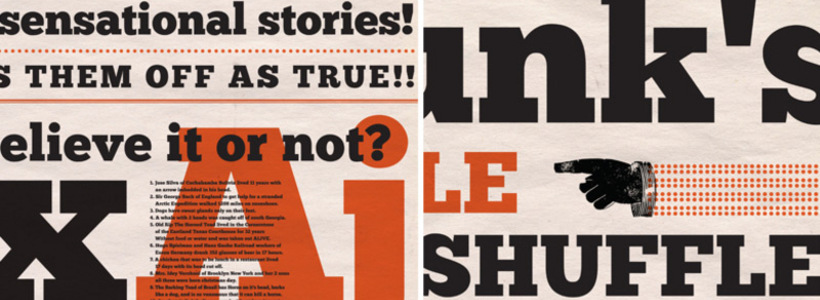
超大膽的 Chunk 引人注目,外觀經典。 被描述為美國西部與報紙標題相遇,最好搭配更纖細的字體。
5. Coolvetica
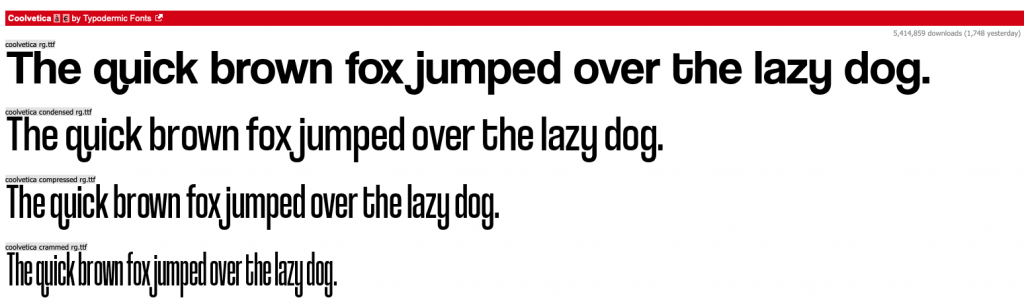
這種對 Helvetica 的俏皮修改具有緊密的間距和時髦的捲發。 該字體是對 1970 年代的致敬,特別是那個時代美國連鎖店的標牌。
6. 新生
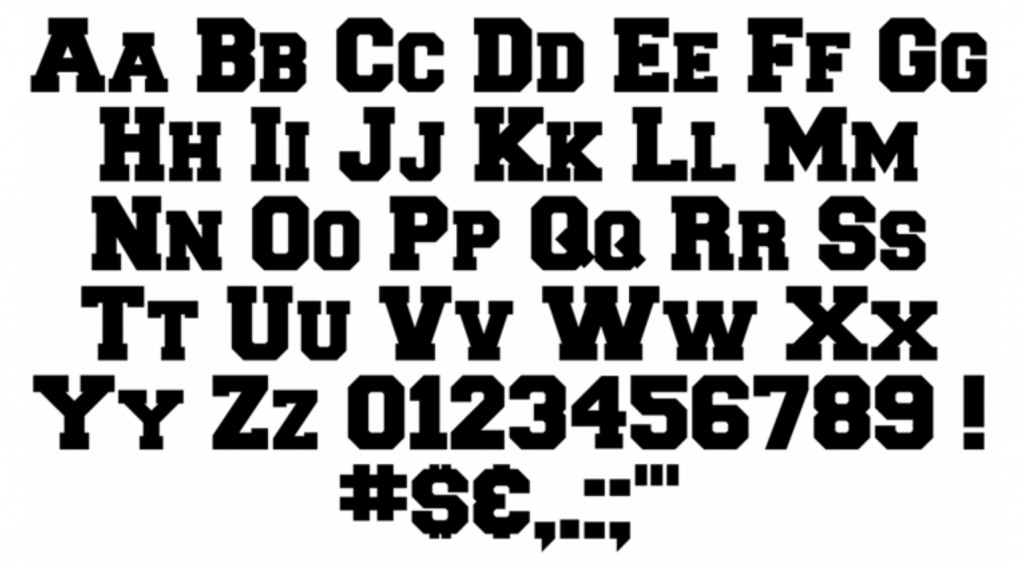
Freshman 是一種簡單的大學風格字體,帶有寬大的粗體字母。 小寫字母在技術上仍然是大寫字母,只是尺寸更小。 如果您想要更苗條的新生版本,請查看美國研究生或高中。
7. 加博
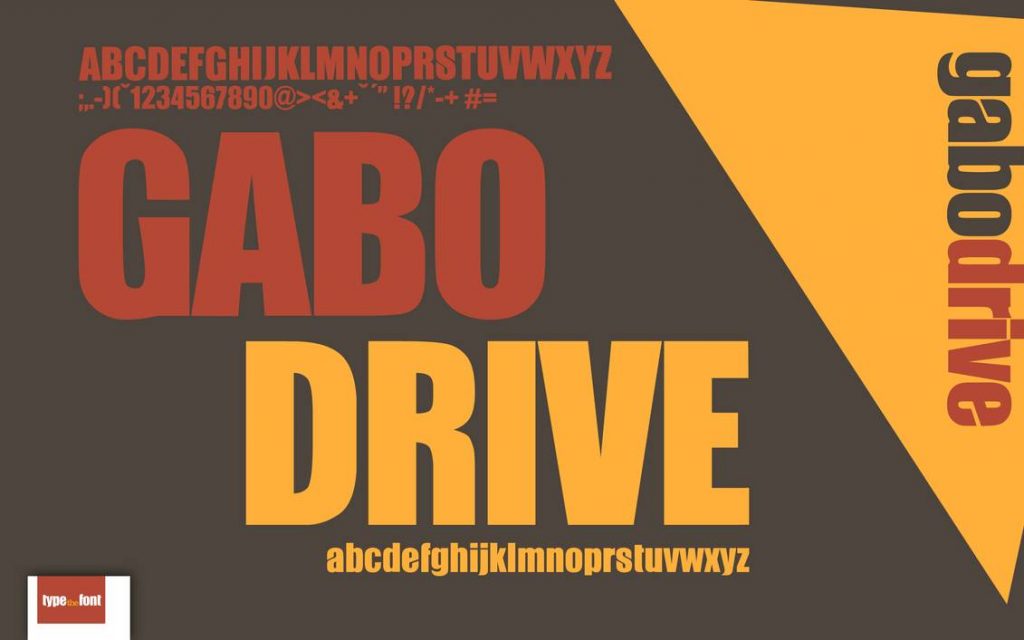
你認為你以前在電影海報上見過加博,也許你見過,但如果你仔細觀察,有些字母會有微妙的傾斜。 在小寫字母中,字母具有平滑的曲線和輕微的裂縫。
8.五大湖
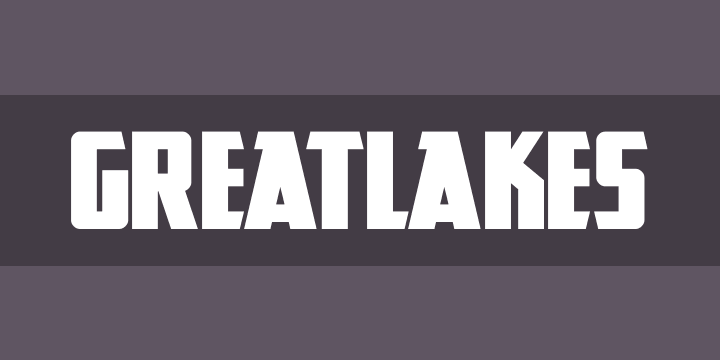
由於某些字母的急劇傾斜和切割,GreatLakes 有棱有角且具有很高的高度和力量,看起來像是在向前走。 它的名字也很完美,你可以在戶外商店的標誌上畫上它。
9. 更高
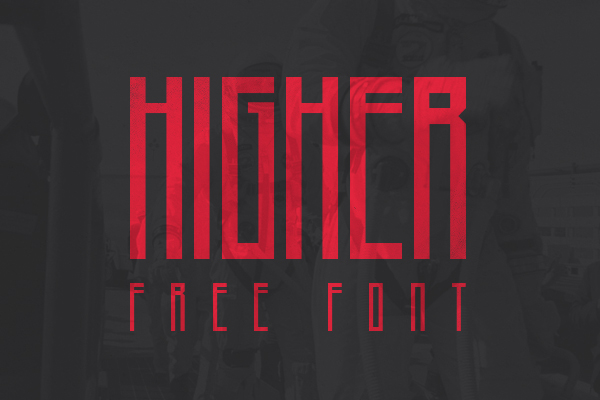
較高是細長和高的,並且字母的識別部分被誇大地高或低。 出於可讀性目的,請確保在確定之前使用此字體測試您的確切副本。
10. 紐波
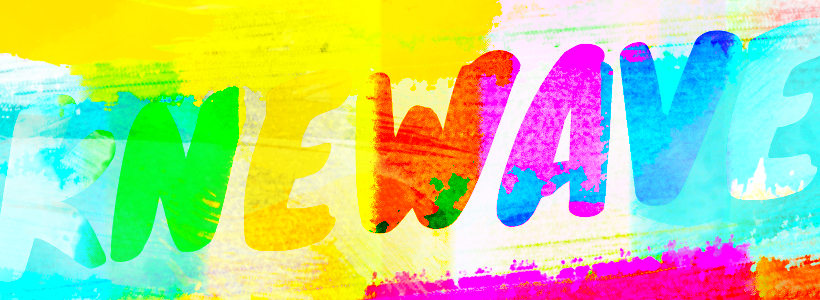
無憂無慮、有趣且大膽,Knewave 是一款適合年輕企業或網站的圓形字體。 這種繪畫字體具有刷狀紋理,沿字母末端最為明顯。
11.小莫田
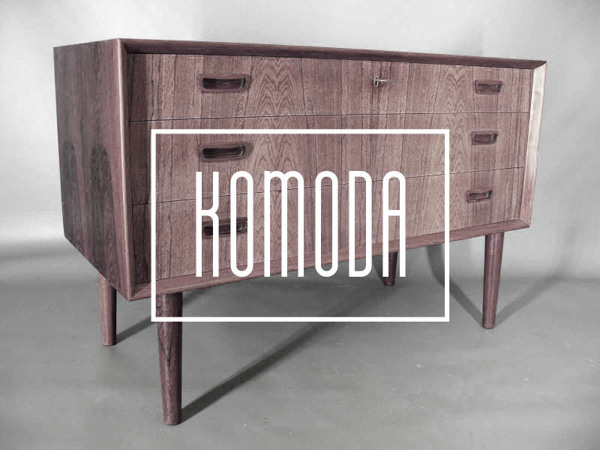
這種窄字體有很多高度,它與短而粗的子標題搭配得很好。 將 Komoda 用於現代或休閒業務,例如極簡主義的家具店或宣傳歡樂時光的酒吧。
12. 馬蒂茲
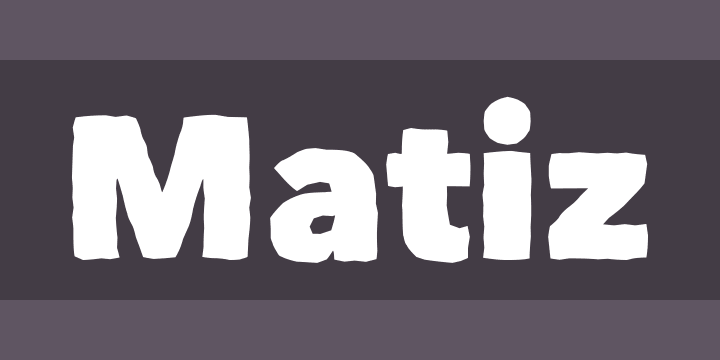
Matiz 搖搖欲墜的手繪質量使它看起來像是在顫抖。 當您想傳達動作或情感時,將其用於品牌或標牌。
13. Megalopolis Extra
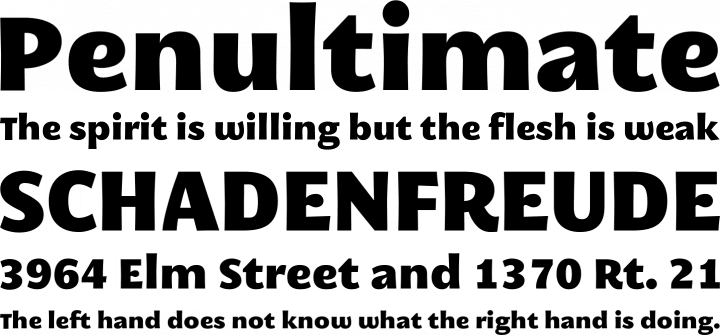
Megalopolis Extra 的字母具有意想不到的曲率,可以柔化原本僵硬的字體。 品牌可以保持大部分傳統,只是一點點個性。
14. 軌道飛行器
Orbitron 有四種重量,看起來像是用於科幻電影海報。 未來主義和幾何,它很容易閱讀,同時仍然很有趣而不是通用。
15.鴕鳥Sans
Ostrich Sans 的脖子很長,有多種款式和重量,包括虛線和圓形選項。 這些變體可以很好地協同工作,您可能不必搜索子標題字體來與之配對。
16. Promesh
毫無疑問,Promesh 具有運動能力,其仿舊網眼外觀讓人聯想到運動衫。 如果您喜歡這種風格但不想要網狀紋理,請下載 Promesh Two。
17. Source Serif Pro
這種基於襯線的字體比其他襯線塊字體更薄。 它優雅且易於閱讀,並且適用於包含大量文本的長橫幅和標題。
18. 暢談
讓人想起 1920 年代的裝飾藝術,Speakeasy 是一種神經質的字體。 尖角與字母的圓形部分形成完美對比,斜體版本傳達運動。
19. 峰會
Summit 是一種懷舊字體,不知何故,它仍然足夠現代,即使是一家科技公司也可以使用。 該字體設計為多種樣式和粗細,旨在分層。
20. 超
戲劇性和強大,Ultra 非常適合強大的標題。 這是一種嚴肅的字體,看起來不會太沉悶,而且總是會產生影響。